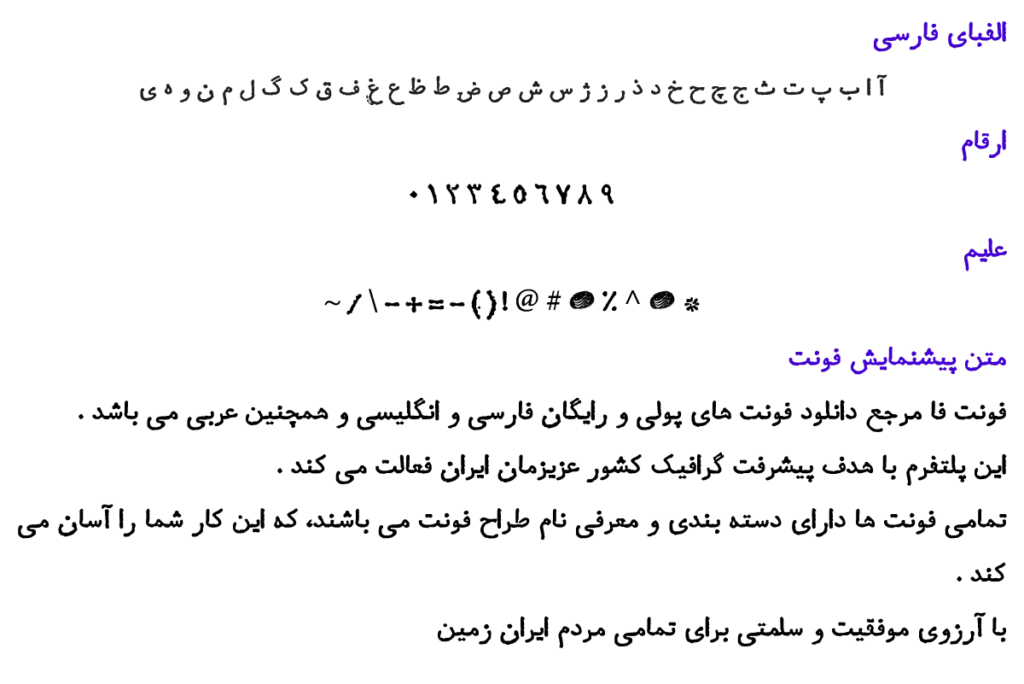
فونت فارسی نفیس – A Nafis
طراح فونت: نوید برهمند نوع فونت: فونت فانتزی
توضیحات و معرفی فونت نفیس
فونت فارسی نفیس ( A Nafis ) از مجموعه فونت های آزاد می باشد، و نیز نوع فونت فانتزی می باشد.
فونت خوشگل مربوط توسط نوید برهمند در سال 1392 طراحی و ساخته شده است.
این فونت بر پایه تایپ فیس ماشین تحریر اولیویتا مدل سال 1975 طراحی شده و در قالب یک پروژه دانشگاهی توسعه یافته است.
و نیز فونت در یک وزن معمولی است.
دموی تایپ فیس معرفی شده را در تصویر زیر میتوانید با شعر زیبای وطن ببینید.